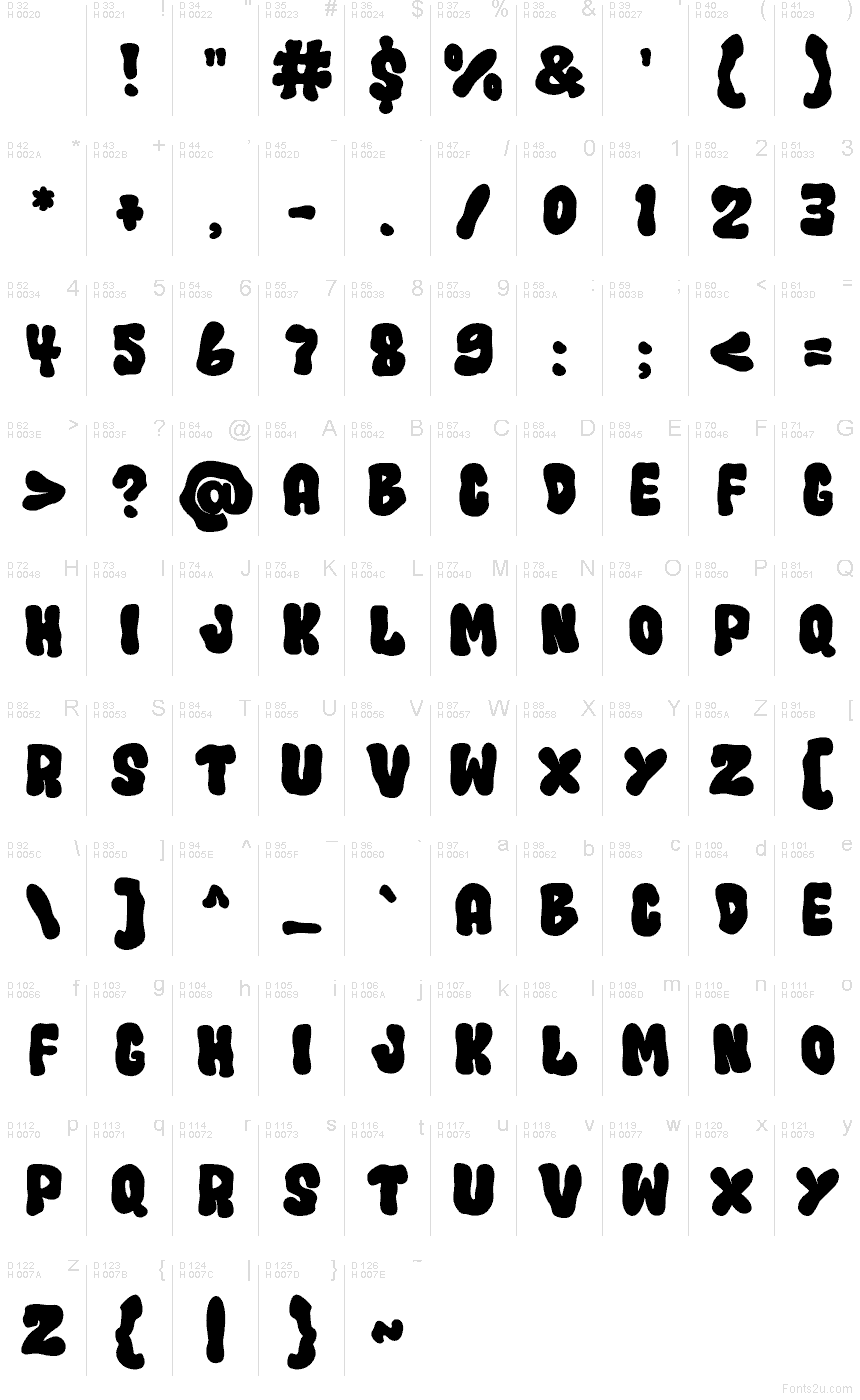
Il font Chunk Wave di Rizal Yusepudin Salman & Muhammad Panji Ramdhani (Cikareotype x Figuree) è un carattere groovy gratuito dalle lettere grandi e arrotondate, che ricordano forme modellate, soffici e leggermente ondulate. Le forme sono piene e compatte, conferendo alle parole un ritmo "blob" divertente e unificato, ben leggibile anche da lontano. È giocoso ma non confusionario, il che lo rende perfetto per titoli audaci e brevi frasi d'impatto.
Utilizza Chunk Wave per poster musicali, flyer di festival, grafiche streetwear, packaging creativi, anteprime di YouTube, adesivi e loghi di ispirazione retrò dove vuoi trasmettere allegria istantanea. Grazie alla sua silhouette spessa e decisa, questo font gratuito spicca anche nelle pubblicità sui social e sulle etichette dei prodotti. Abbinalo a un carattere sans serif pulito e stretto per il testo principale e aggiungi un po' di spaziatura quando vuoi che il design respiri con vivacità.